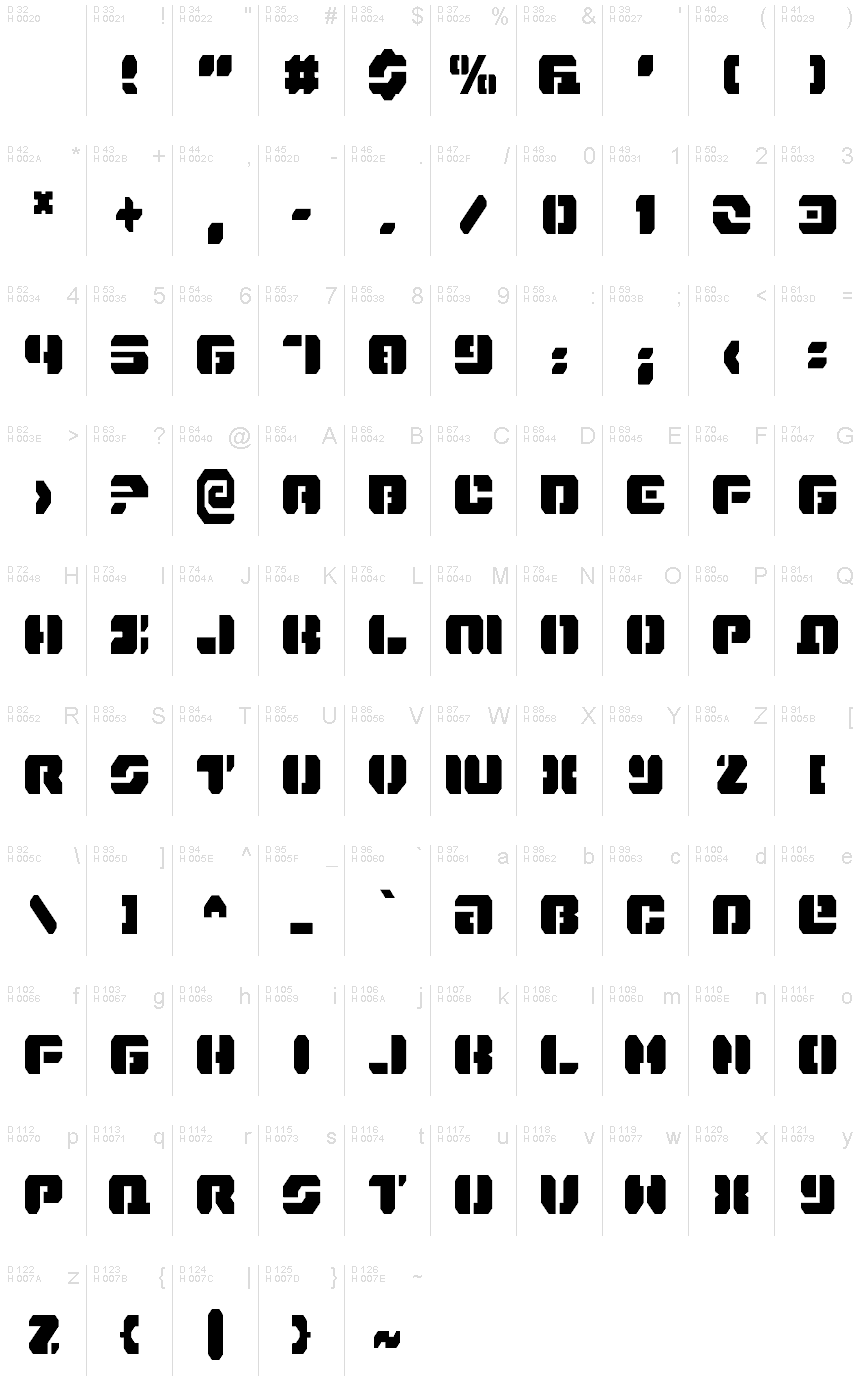
Dan Stargate Condensed di Iconian Fonts è un carattere display futuristico gratuito, solo maiuscolo, con un'estetica decisa che richiama i poster di fantascienza. Le lettere sono alte e strette, ricavate da blocchi geometrici massicci con tacche affilate, angoli smussati e alcune interruzioni in stile stencil che conferiscono al font un aspetto progettato, quasi tecnico.
Si adatta perfettamente ai loghi di videogiochi, titoli di film, branding per e-sport, copertine di album e grafiche per eventi tecnologici, dove le parole brevi richiedono un impatto denso e salvaspazio. Essendo un font gratuito, funziona bene anche per titoli di copertina, monogrammi e intestazioni dal sapore di interfaccia, poiché le maiuscole compresse mantengono i layout compatti mentre i tagli angolari fanno gran parte del lavoro di stile.